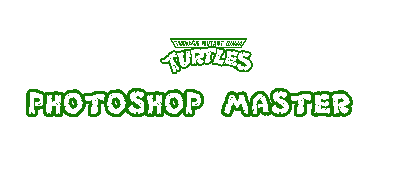
Круто)
Ваще круть!!
черепашки нинзя)))
Ищите шрифт под названием ljTurtlesTMNT (Bold Cyrillic) (начертание: Английский+Русский) (со внутренней заливкой, а не по контуру. Контур можно добавить самим в любой момент)
Вспомним детство))))))
КЛАССНо)
Ааааа!!! Черепашки-ниндзя,йа вас люблю)))))))))))
Старые добрые черепашки-ниндзя!:)